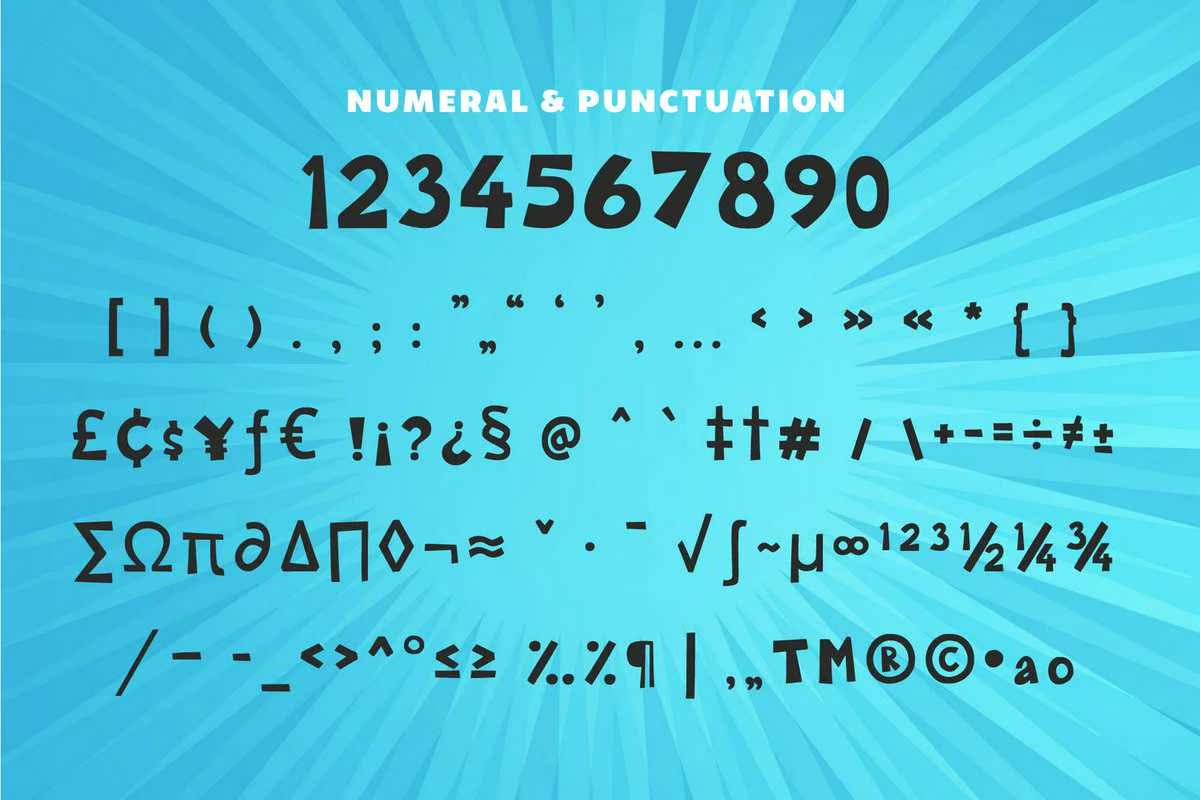
ShapedCornerFontHandRittenstyFonts,适合儿童的Med设计。适用于儿童的ToryBooker、品牌项目、徽标、婚礼设计、社交媒体、广告、产品包装、产品设计、标签、照片、水印、邀请、文具和需要手写品味的所有项目。ShapedCornerFontHandRittenstyFonts,适用于儿童的医疗设计。完美适用于儿童的托儿所、品牌项目、徽标、婚礼设计、社交媒体、广告、产品包装、产品设计、标签、摄影、水印、邀请函、文具和需要手写品味的任何项目。